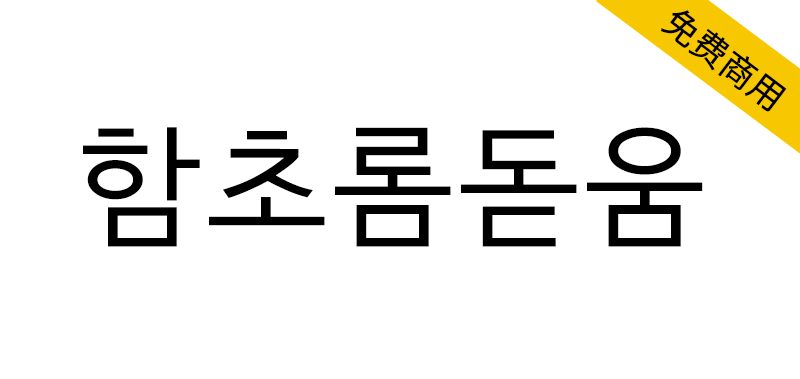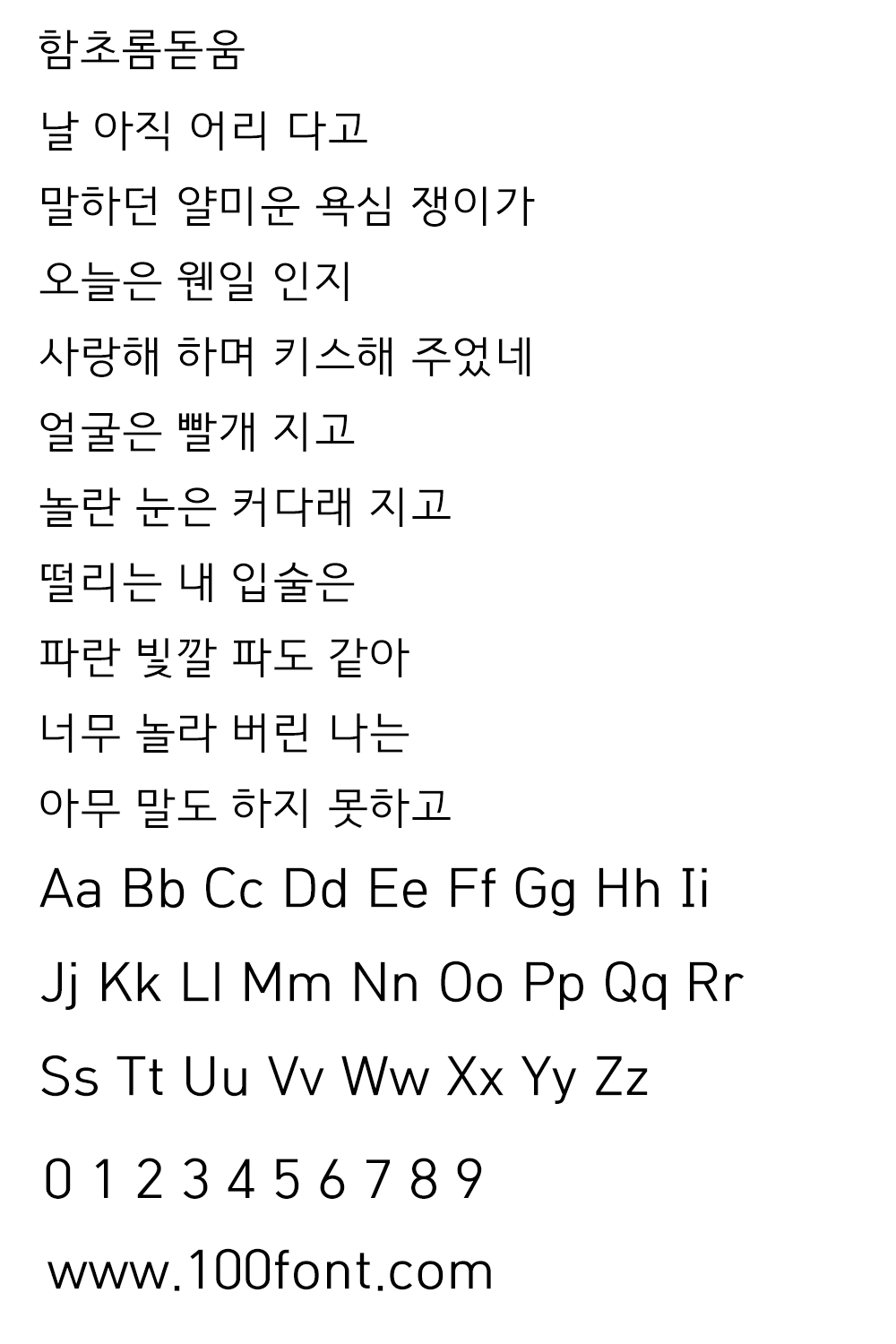
함초롬돋움是一款韩国旧字形免费商用黑体字体。通过将GSUB / GPOS信息放入Hangul and Computer Corporation的Hamchorom字体中,由韩国技术学会重新分配了该字体,主要目的是在一开始就正确处理旧的韩文,它还具有附带的目的,以使其更容易使用字体中包含的字典药物。
한글과컴퓨터사의 함초롬 글꼴에 한국텍학회가 GSUB/GPOS 정보를 집어넣어 재배포하는 글꼴입니다.
주 목적은 첫가끝 옛한글의 올바른 처리를 위한 것입니다.
글꼴에 포함된 사전식 약물을 쉽게 사용하기 위한 목적도 부수적으로 가집니다.
이 글꼴을 사용하면 한컴오피스에서만 예쁘게 보이던 함초롬체 옛한글을 GSUB를 지원하는 모든 어플에서도 예쁘게 볼 수 있게 됩니다.